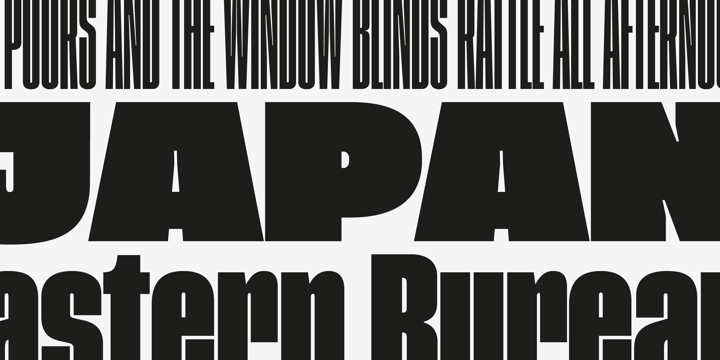
Кристиан Шварц: «Когда шрифтовые дизайнеры становятся знаменитостями, это немного смешно»
Разговор с Кристианом Шварцем, в котором он отказывается быть знаменитостью, обозначает несколько важных тенденций современного шрифтового дизайна и отвечает на вопрос: «Какой шрифт самый „сегодняшний“?».
Илья Рудерман: Как бы ты сформулировал для себя последние тенденции шрифтового дизайна?
Кристиан Шварц: Главная тенденция сегодня — фрагментаризация. Раньше для разных целей использовались разные шрифты. Книжными шрифтами набирались книги, газетными — только газеты, особые шрифты существовали для вывесок. Но в 1970–80-е годы и особенно с распространением цифровых шрифтов функциональные различия стали сглаживаться. Шрифтом ITC Garamond, например, можно было набирать и книги, и журналы, и газетные заголовки, а загрузив в плоттер, его можно было использовать в вывесках и на телевидении.
Обложка журнала ‘W’ со шрифтом Мигеля Рейеса (Miguel Reyes)
Разворот из журнала ‘W’ со шрифтом Мигеля Рейеса (Miguel Reyes)
Я считаю это и есть самый сильный тренд на сегодня. Проекты снова могут быть гиперспециализированными. Вы можете создать экранный шрифт для чтения поэзии для Академии Американских Поэтов, и в то же время по-прежнему создавать большие семейства для газет и журналов.